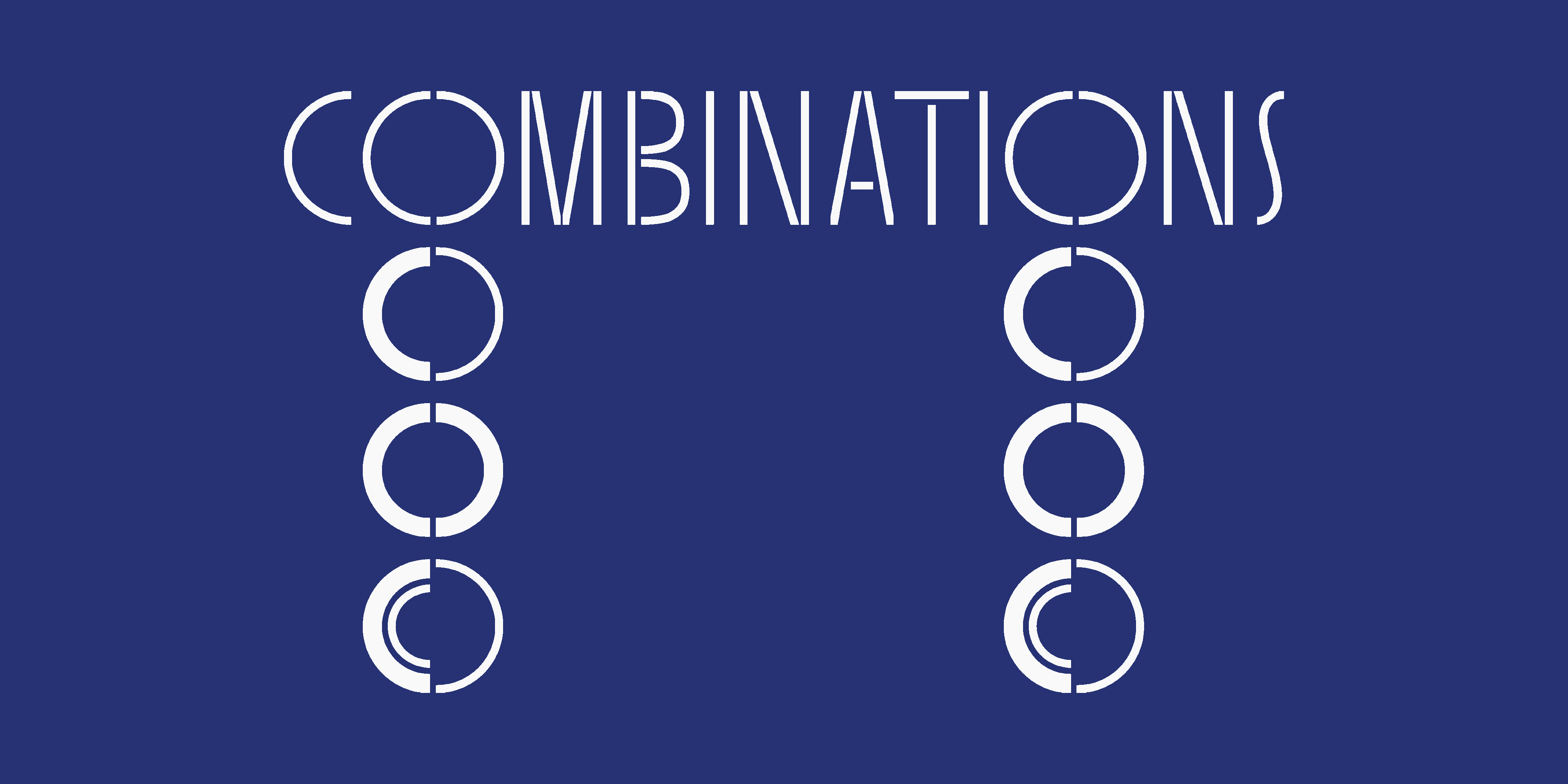
Sisters est un ensemble dynamique de polices d’affichage au pochoir conçues par Laura Meseguer, co-fondatrice de Type-Ø-Tones. La famille comprend quatre nouvelles polices qui partagent des principes fondamentaux de construction et se complètent, comme le font les sœurs, en célébrant leurs différences. Les variations de contraste, de graisse et de caractéristiques de conception se traduisent par quatre styles distincts allant de Sisters One à Sisters Four. Ce quatuor sympathique ne contient pas de minuscules, affirmant la place légitime de la famille dans l’espace typographique du titrage. Sisters est un hommage à toutes les femmes créatives de ce monde.